Sử dụng Font chữ đúng cách trong bố cục thiết kế web
Một số người nói rằng kiểu chữ là một xu hướng thiết kế web của năm. Kiểu chữ luôn luôn là điều cơ bản để thiết kế. Trong nhiều thế kỷ, văn bản đã được sử dụng để giao tiếp và truyền thông điệp hiệu quả. Cũng vì vậy mà chọn kiểu chữ cho thiết kế web bao giờ cũng là một kỹ năng mà sẽ không bao giờ trở nên lỗi thời.
1. Purple Orange
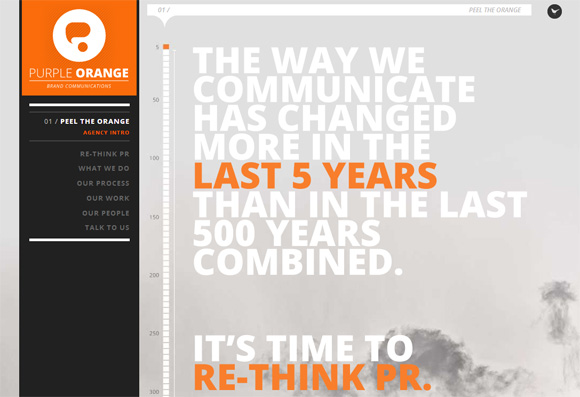
2. Polar Gold
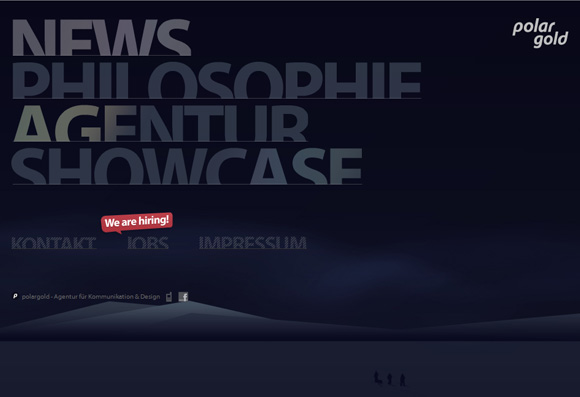
3. Made by Water
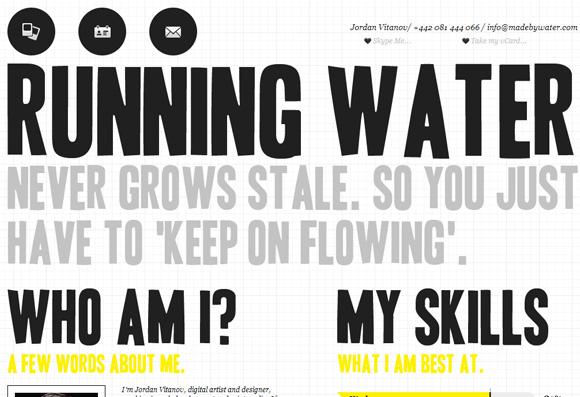
4. Kidd81
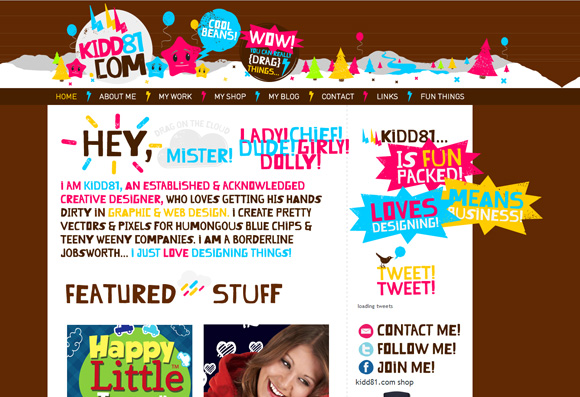
5. Kansas City Creepfest
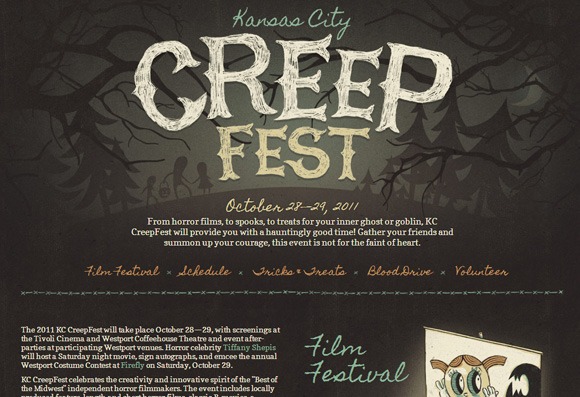
6. Austin Eastciders
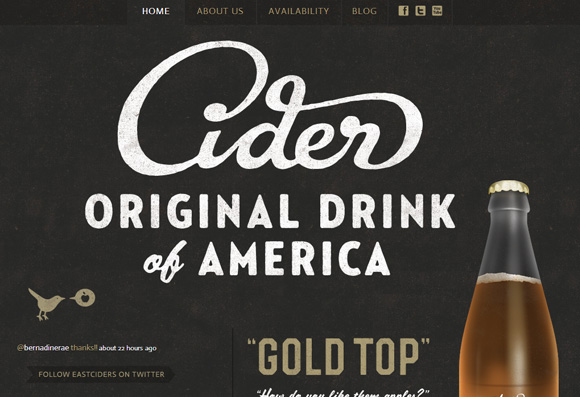
7. CIRQ
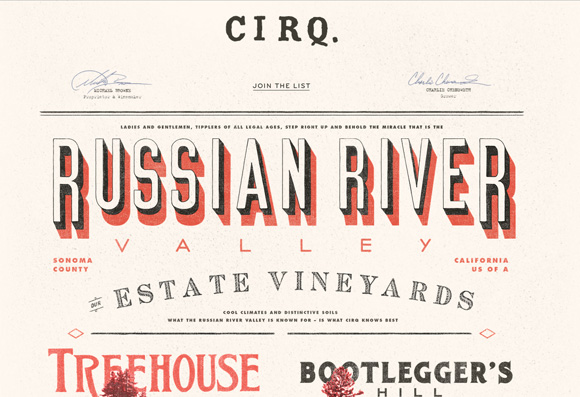
8.Psych & Psych
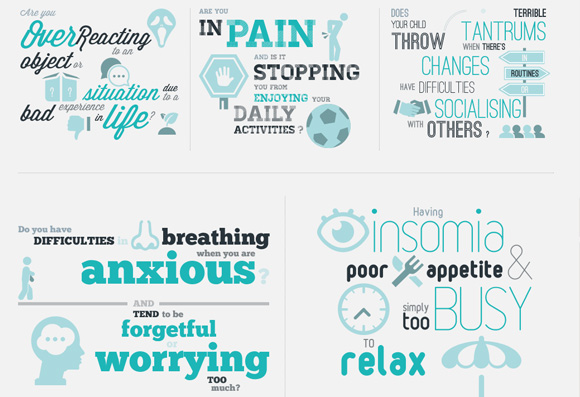
9. Lost Type
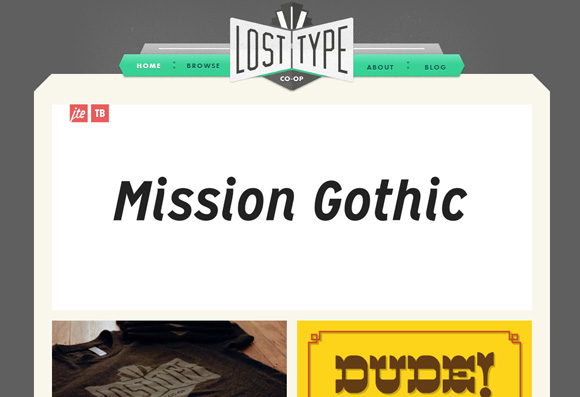
10. Elysium Burns
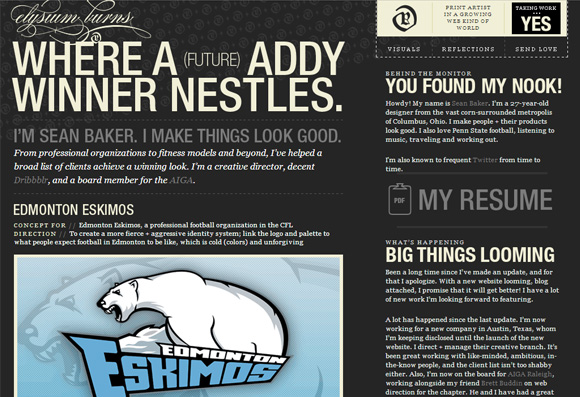
11. NATL
12. Ryan Keiser
13. Just Dot
14. Earth Hour
15. Stephen Caver
16. Handiemail
17. Tapmates
18. La Bubbly
19. Rob Edwards
20. Von Dutch